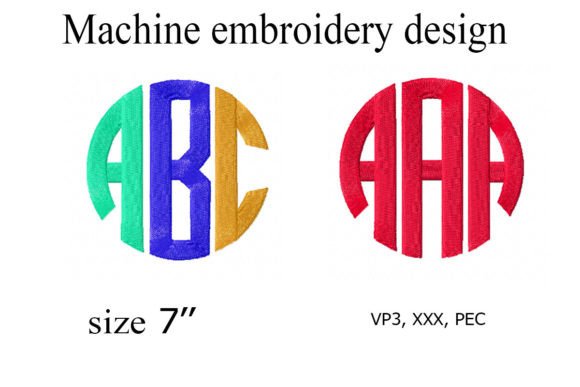
Circle Monogram
์ •๋ฐ€ํ•˜๊ฒŒ ์ œ์ž‘๋œ Circle Monogram๋Š” ๊น”๋”ํ•œ ๋ฒกํ„ฐ, ๋ถ€๋“œ๋Ÿฌ์šด ํƒ€์ดํฌ๊ทธ๋ž˜ํ”ผ ๋ฐ ์•ˆ์‹ฌํ•  ์ˆ˜ ์žˆ๋Š” ์ƒ์—…์šฉ ๋ผ์ด์„ ์Šค๋ฅผ ์ œ๊ณตํ•ฉ๋‹ˆ๋‹ค.